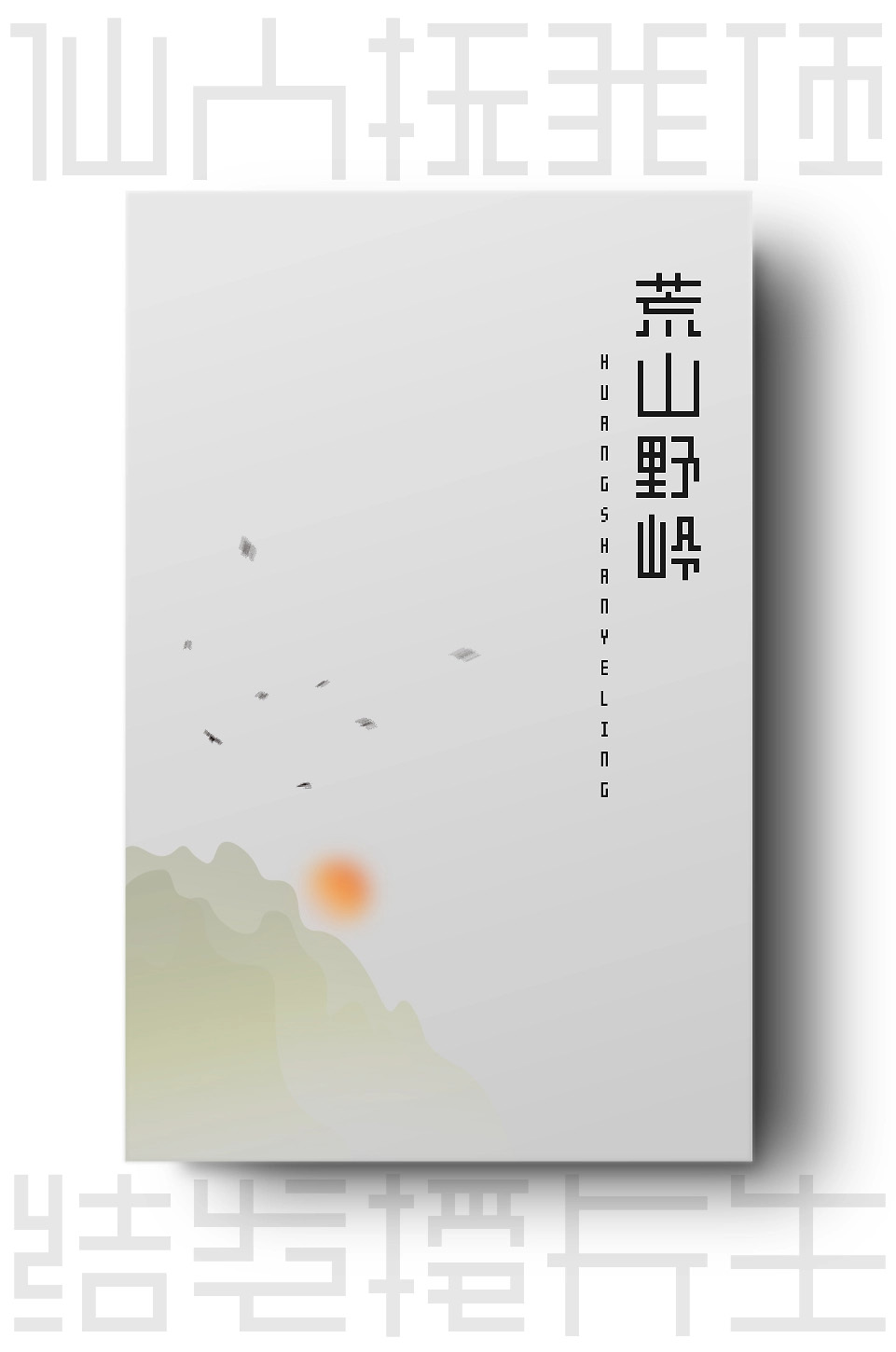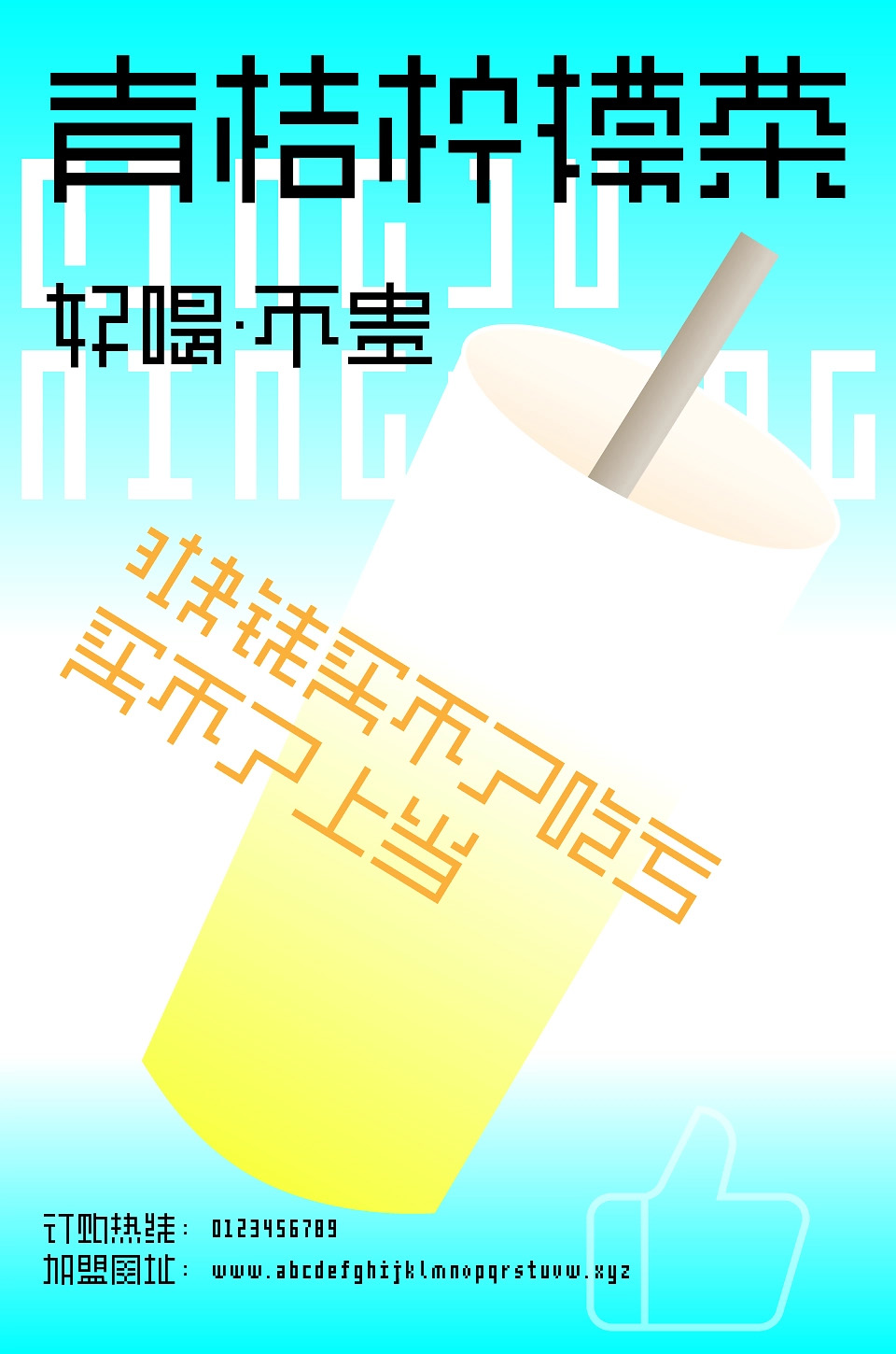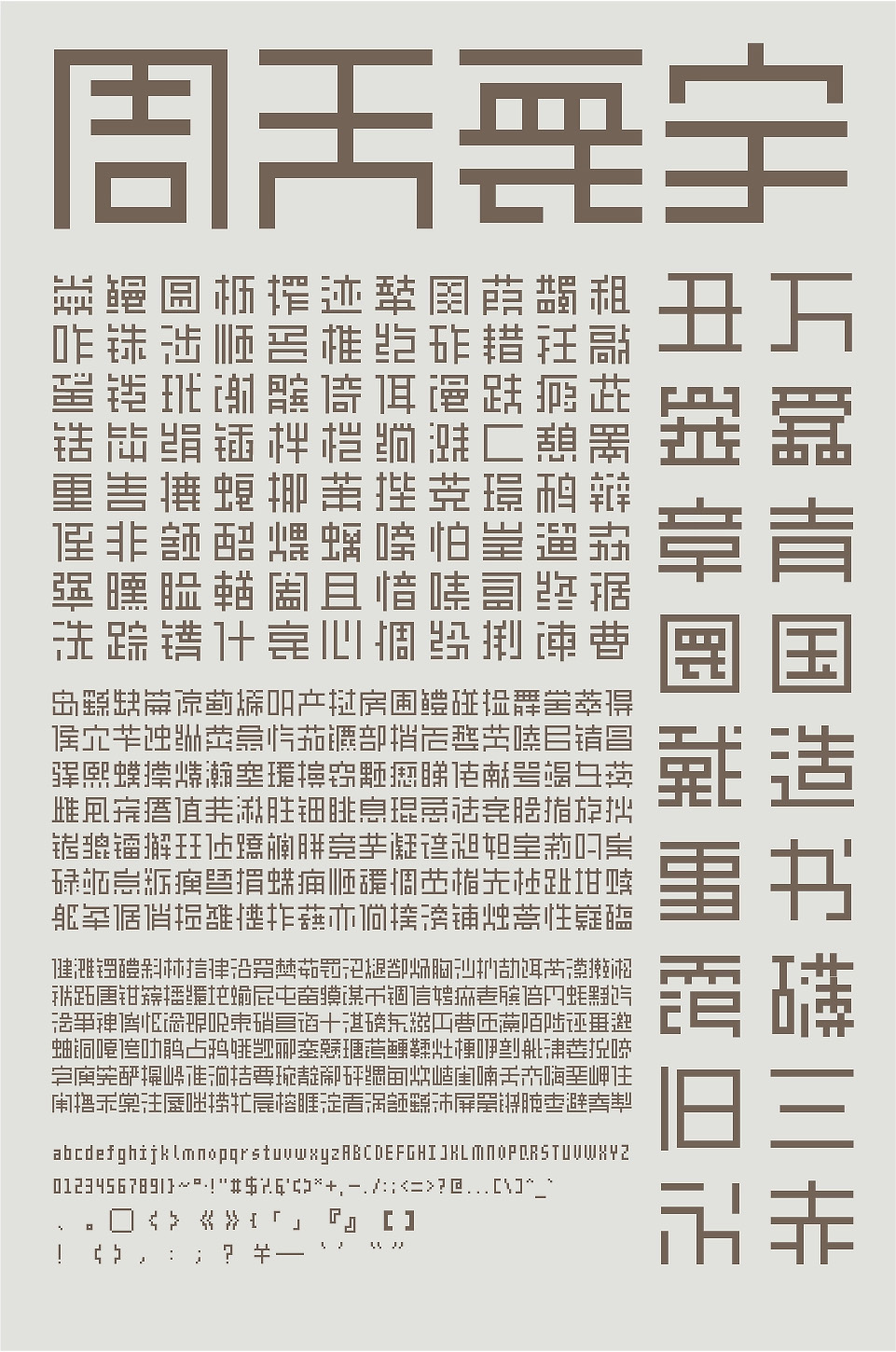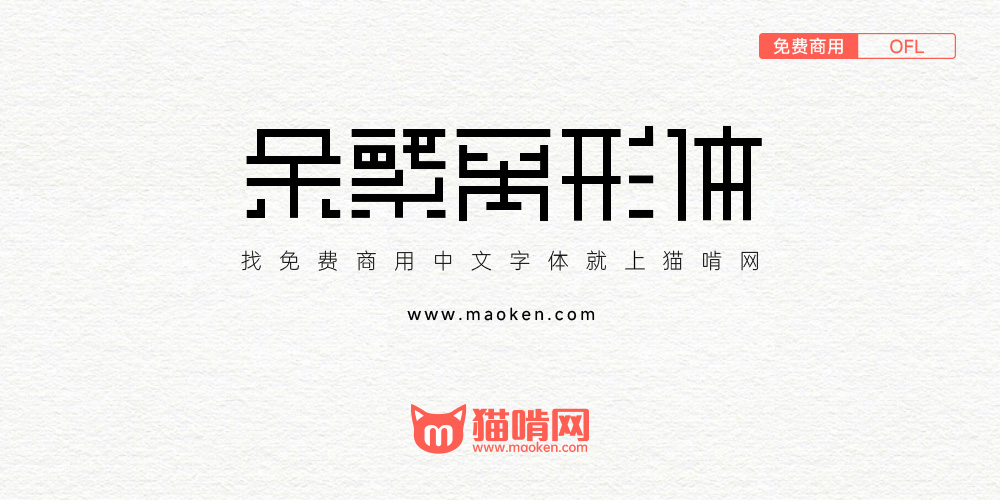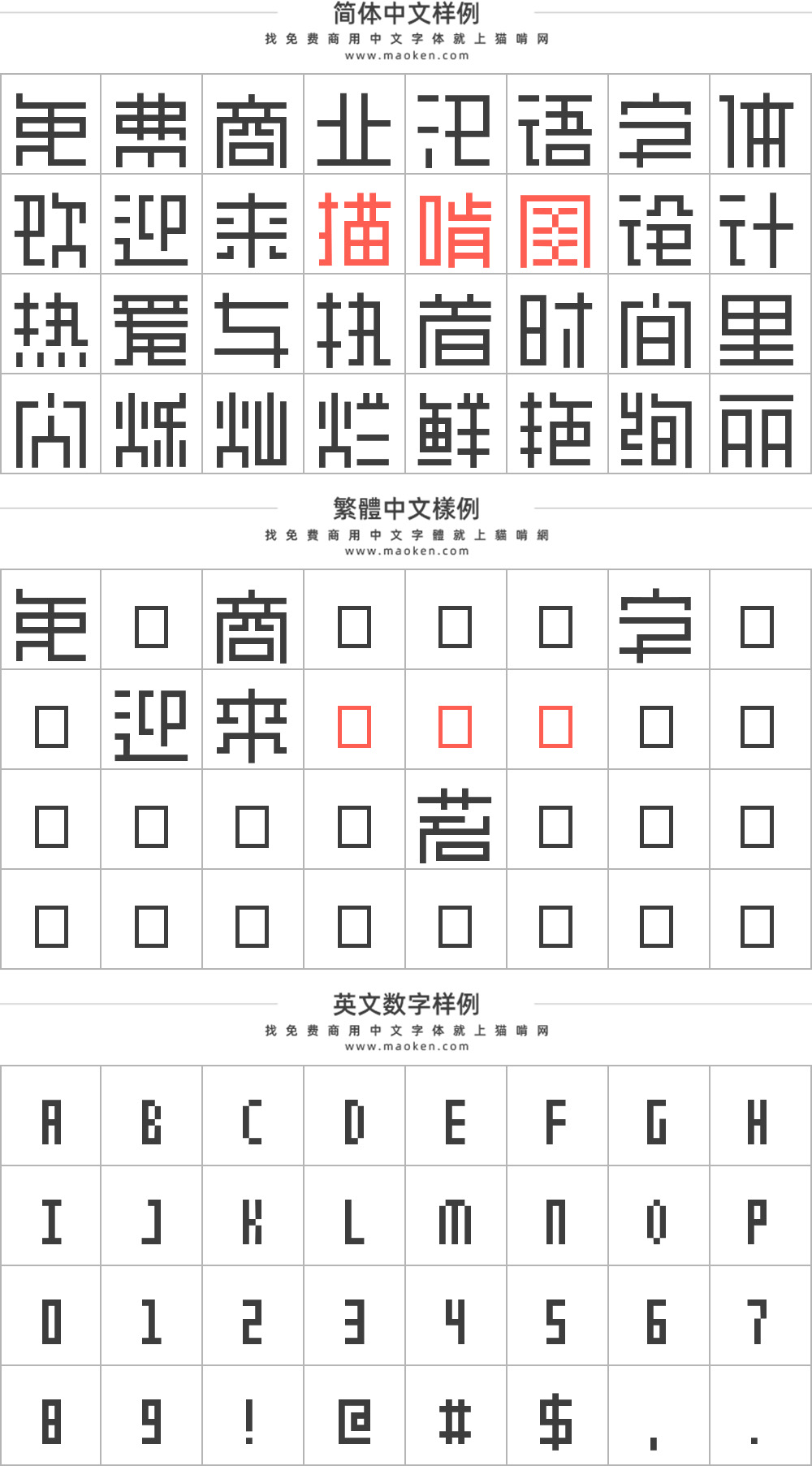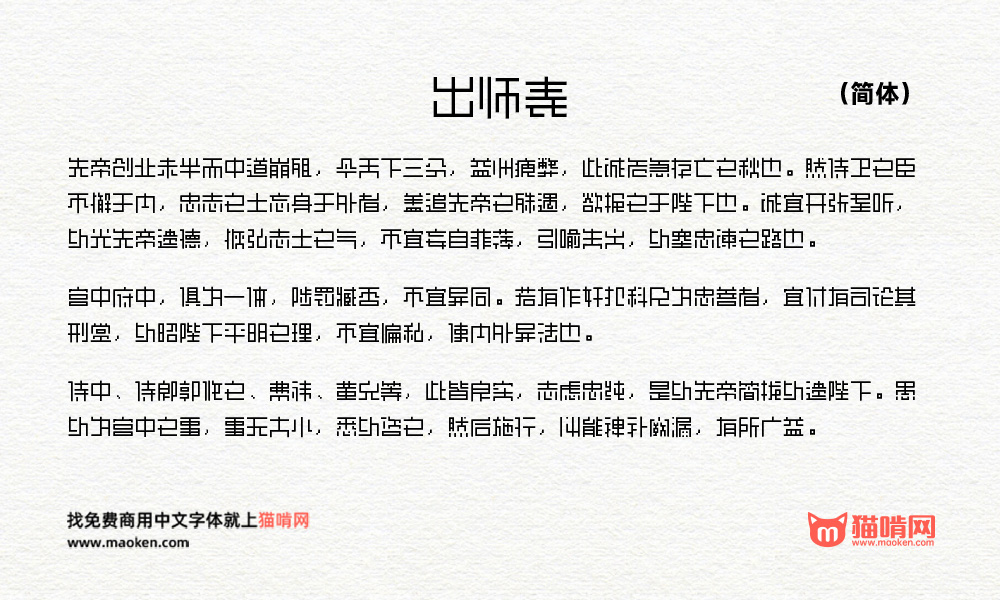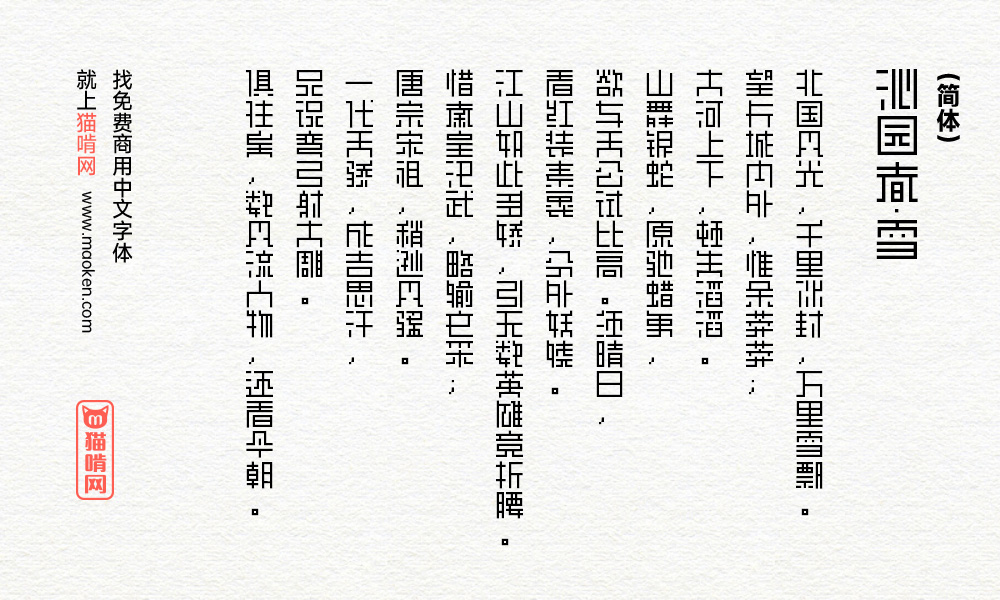
余繁离形体:这是一款类像素体的字体 开源OFL免费商用
字体作者:余繁 (中国大陆) 字体字重:1个
这是一款类像素体的字体。
与像素体相同之处为——
1)以笔画宽度为基准,有最大尺寸限制(11X11);
2)笔画由点与横竖线构成。
由于存在尺寸限制,对于复杂的字型必然是要简化的。其简化策略为:优先在保持部件外围结构的情况下简化部件的笔画(例:目→日→口),其次才会考虑改变复合部件的结构(例:吕→日)。
简化字型会导致字型辨识度降低(也可以说是错误字型),若是着实不能接受,请谨慎考虑是否使用。
我这里奶茶店、汉堡点、冰激凌店招牌好多都用这个字体,在maoken才知道是什么字体
如果有繁体就完美了!
• 这个字体好像不适合繁体,因为繁体笔画太复杂了,所以不合适
用在像素游戏里面感觉很合适
想起日系的东亚重工字体和真四角書体